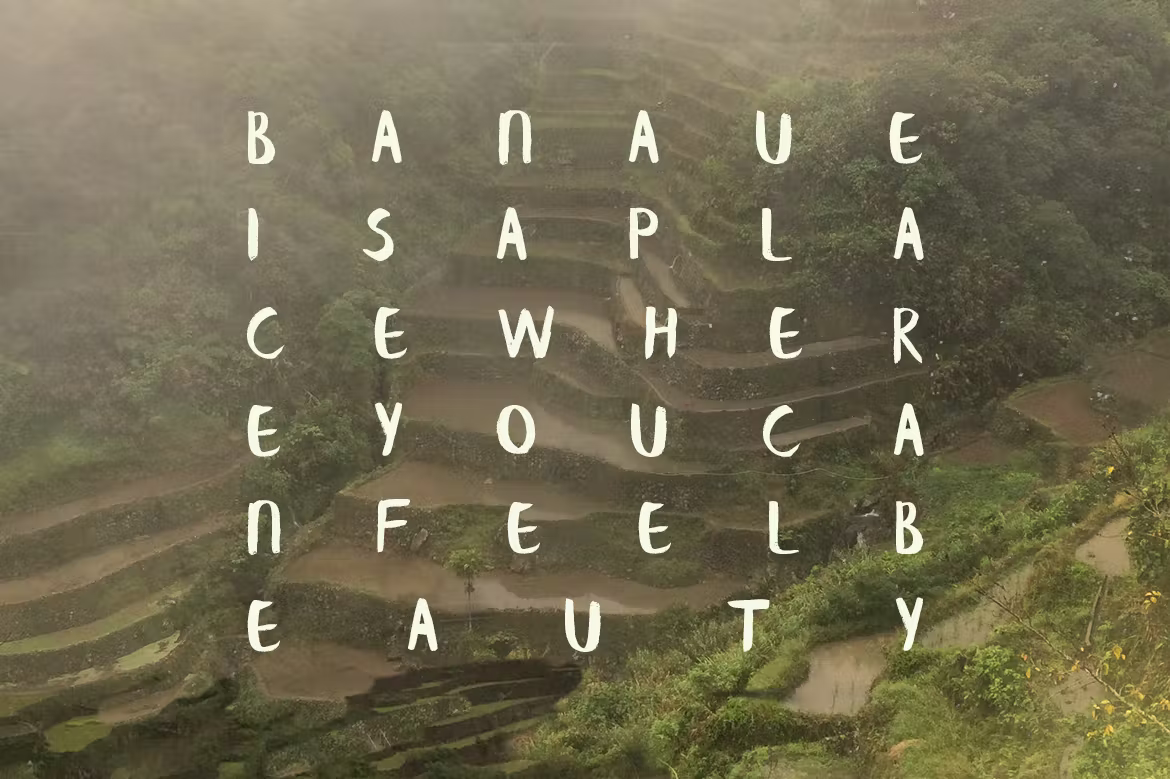
Banaue Handwritten Brush Font
Description de Banaue Handwritten Brush Font
Banaue est une police de pinceau manuscrite pour un look fait maison. La police comporte 104 caractères et tous les glyphes de base. Le téléchargement contient un fichier .otf. Brossé à la main par Ieva Mezule. Le nom vient de Philippenes, Banaue est un lieu du nord. Des rizières en terrasses qui s’étendent autour des montagnes et le riz qu’elles produisent est uniquement destiné à l’usage local. La dame à l’imperméable bleu, qui apparaît sur l’image principale, était une planteuse de riz locale.
Vue de la police du pinceau manuscrit Banaue